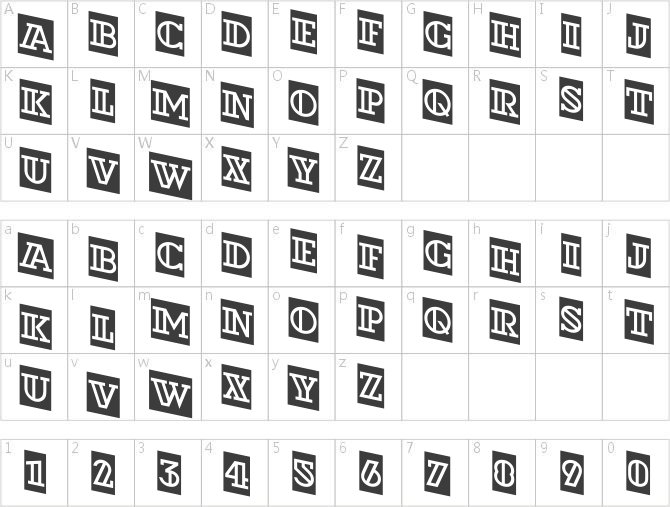
a_DexterDecorCmDn
a_DexterDecorCmDn介紹
a_DexterDecorCmDn字體字庫是一款讓人賞心悅目、百看不厭的英文字體,適合各類廣告和產品包裝設計應用,字體大小0.03MB,格式為ttf字體,上傳用戶是浪跡天涯,作者/版權方為未知
a_DexterDecorCmDn效果圖